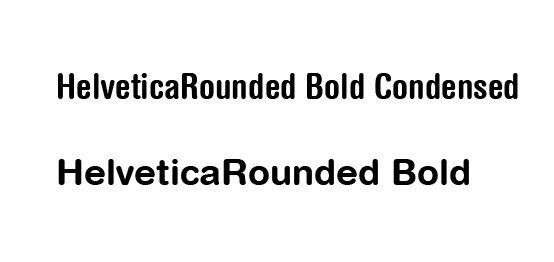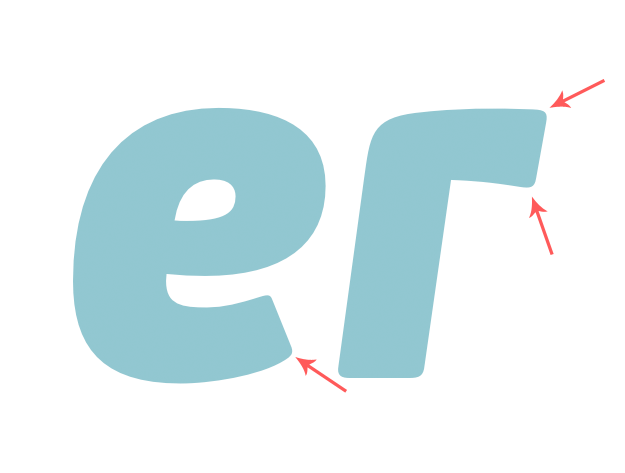
Eine rounded - aber mit kyrillisch bekannt?
ich wäre -- als Autodidakt ;-) im Grunde mit der Helvetica Rounded Condensed, im Grunde genommen auch mit der VAG Rounded (aber irgendwie zu wenige Schnitte) zufrieden, jedoch... Ich brauche unbedingt den kyrillischen Zeichensatz.
Irgendwie "rounded", mit Light, Regular, Bold und Condensed ausgestattet, Kostenpunkt bis 200 EUR, ist das was ich suche.
Was ist euch da bekannt?
Falls gar nichts geht überlege ich die Vida zu nehmen.
Ist mir aber irgendwo zu "trendig". Serifenlose Alternativen mit seltener anzutreffender Anmutung sind willkomen.
das ist wirklich ein strenges kriterium, das nur wenige schriften übrig lässt.
bei linotype gibt es die vag rounded in vier gewichten mit kyrillischem zeichensatz. alternativen, die ebenfalls keine condensed-schnitte haben, wären houschka rounded, chevin, ff din round oder sommet rounded. bei storm könntest du dir noch die etelka anschauen, die auf mich etwas runder wirkt als die vida.
hab auch mal ein auge auf die windows-vista/7-systemschrift calibri, zu der meines wissens demnächst weitere schnitte veröffentlicht werden sollen.
Alle gewünschten Styles sind zwar nicht drinnen, aber sieh dir die Beau Sans von Parachute an. Und einen griechischen Zeichensatz hat sie auch, falls der Kunde in einen Hoffnungsmarkt (wörtlich) expandieren will … :-D
Ansonsten ist Paratype eine bekannte russische Foundry.
Die BeauSans hat es mir sehr angetan. Ich denke sie ist bei größeren Textmengen leserlicher / ruhiger als die Sommet (es handelt sich meist höchstens um 2-3 Absätze, das meine ich damit. Kann man dazu schon "Fließtext" sagen?).
Aber wichtiger: die "Ecken" sind abgerundet.
Das ist es was ich mit "rounded" meinte. Wie sind da die Begrifflichkeiten wenn ich diese Eigenschaft einer Schrift korrekt bezeichnen möchte?